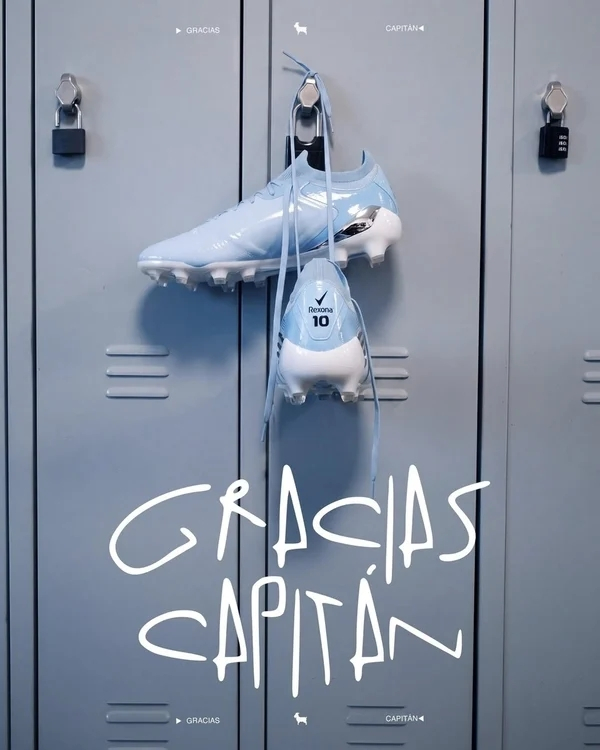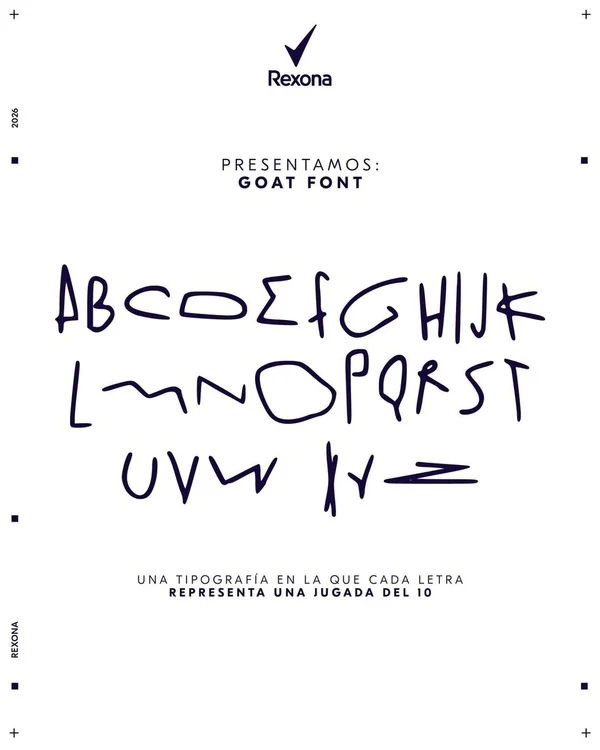
Аргентинское подразделение Rexona необычным способом отдала дань Лионелю Месси, завершившему карьеру в национальной сборной. Бренд превратил движения футболиста на поле в полноценный шрифт. Проект получил название GOAT Font, где GOAT расшифровывается как Greatest of All Time.
В основу каждой буквы легли реальные игровые движения Месси: финты, ускорения, смены направления и траектории ведения мяча. Дизайнеры перенесли их с футбольного поля в графическую форму, превратив характерные перемещения футболиста в алфавит.
При этом Rexona не раскрывает, какие именно матчи и игровые эпизоды использовались при создании отдельных букв. Это стало частью концепции кампании: поклонникам предлагают самостоятельно сопоставлять элементы шрифта с архивными моментами карьеры Месси и угадывать, какое движение легло в основу той или иной буквы.
Креатив появился на фоне завершения Месси выступлений за сборную Аргентины. Футболист дебютировал за национальную команду в 2005 году и вместе с ней выиграл Кубок Америки в 2021 и 2024 годах, а также чемпионат мира в 2022-м.